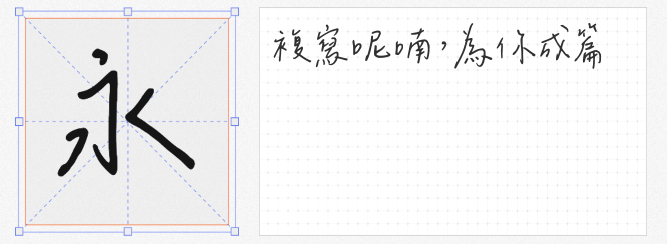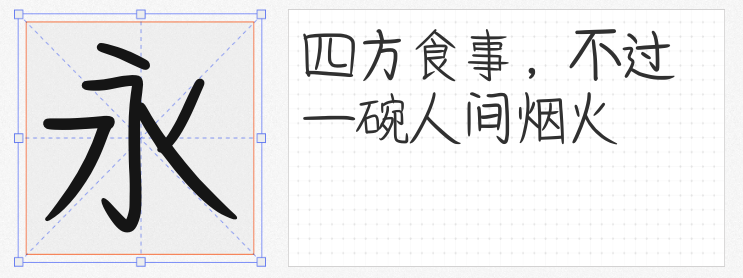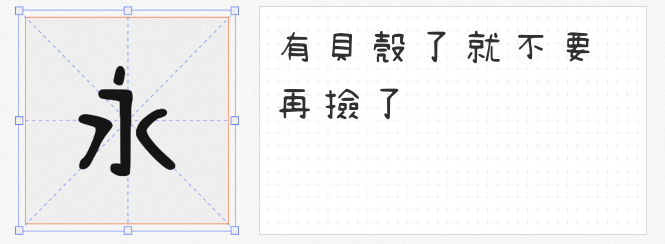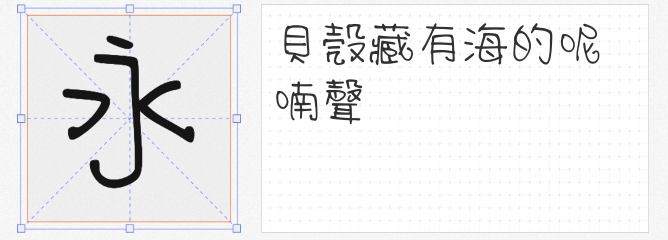
在数字设计追求效率的当下,手写字体的独特质感成为打破同质化的关键。本文精选四款风格迥异却均支持免费商用的手写字体,从校园创作到设计师开源项目,覆盖繁体与简体场景,为品牌视觉、文化创意等领域提供多元选择。
由学生王立宇与韦辰共同创作的辰宇落雁体,灵感源自“沉鱼落雁”的谐音。这款字体通过版本优化后呈现纤细灵动的笔触,仿佛将字词封存在时光胶囊中。其字形带有自然的手写颤动感,尤其适合应用于专辑封面、明信片及绘本设计。尽管简体字符覆盖率有限,但在繁体文化场景中,它能精准传递“永恒召唤”的诗意氛围。
国内设计师lxfly2000在B站FontForge教学期间发布的Acy手写体,以SIL Open Font License 1.1协议开源。这款字体兼顾手写温度与屏幕显示清晰度,笔画粗细过渡自然,特别适合报纸杂志标题、品牌标志及海报设计。其字符集覆盖GB2312标准,能满足大部分简体中文商用需求,成为设计师工具库中的“安全牌”。
台湾设计师游清松以原子笔在稿纸书写初稿,通过“守写字”网站数字化后,再经字体软件雕琢出清松手写体系列。第6代版本以圆润的笔画转折和均匀的字重,营造出俏皮可爱的视觉效果。该字体支持中英双语及符号数字,在社交媒体图文、儿童品牌包装等场景中,能快速拉近与受众的情感距离。
作为系列早期作品,清松手写体3以更强烈的手写可爱风格脱颖而出。尽管简体中文支持较弱,但其在繁体中文环境下的表现堪称典范:笔画间保留书写时的连笔痕迹,如“心”字底部的勾挑设计,为传统文本注入现代活力。这款字体尤其适合文创产品标签、手账模板等需要凸显个性的细分领域。
这些手写字体承载着创作者的温度,更以开放姿态赋能商业设计。选择它们,即是选择让每个字符都成为传递情感的媒介。